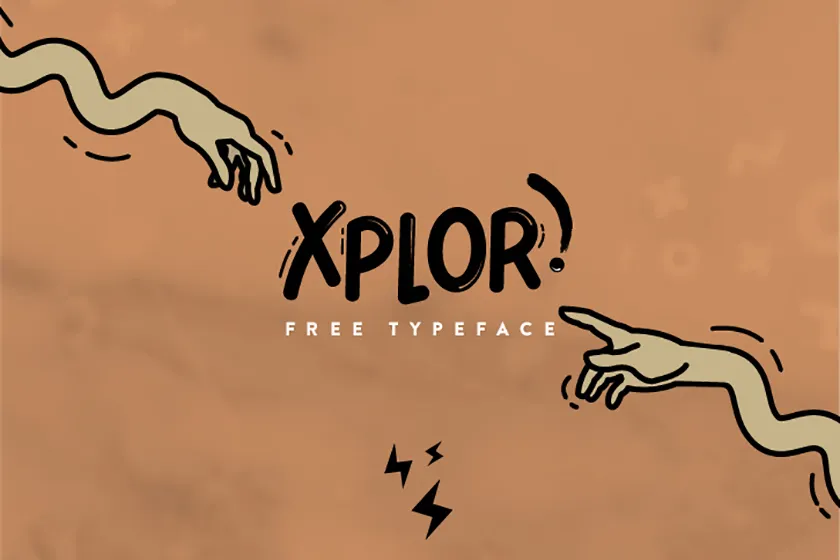
Xplore Typeface – Fonte Grátis
Xplore Typeface
Xplore é uma fonte tipográfica que tem características peculiarmente divertidas, fazendo-a se destacar em meio a outras fuentes. Esta fonte é perfeitamente adequada para quem deseja diferenciar seu design, citações, posters ou logotipos e lhes dar o centro de atenção. Xplore foi projetada não apenas para quebrar padrões convencionais, mas também para provocar risos e tornar a comunicação visual mais dinâmica. Com sua personalidade única, essa fonte é perfeita tanto para os profissionais como para quem usa as fuentes em casa. Ela é livre de uso comercial e pessoal, permitindo que você utilize esta fonte nos seus projetos sem preocupações. Para aqueles que valorizam uma dose de humor e criatividade na sua tipografia, Xplore é a opção perfeita.